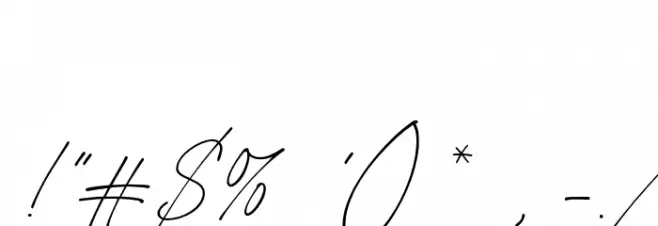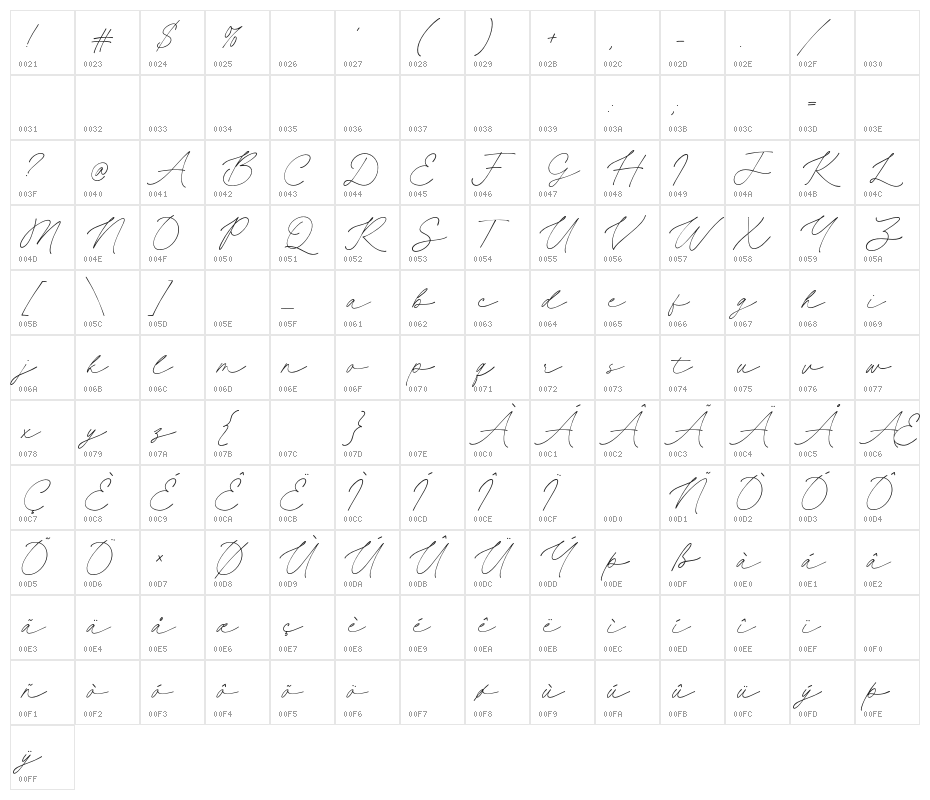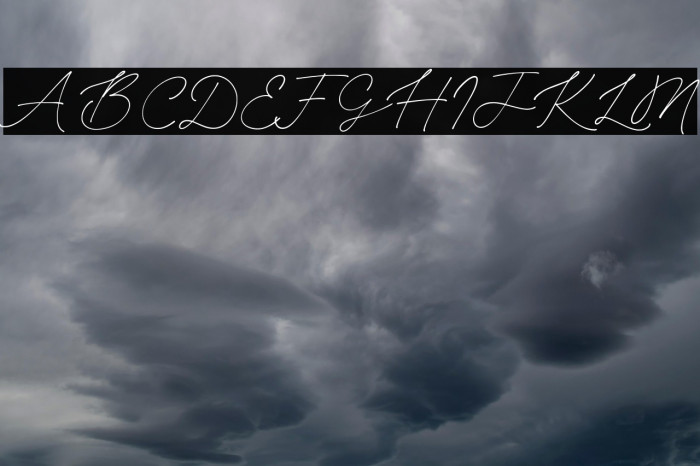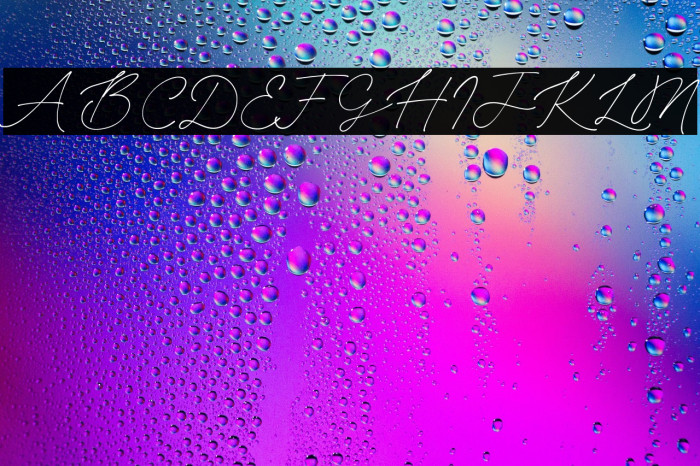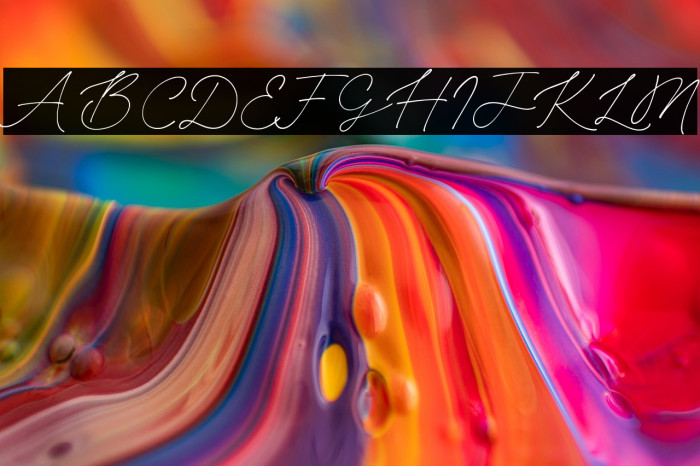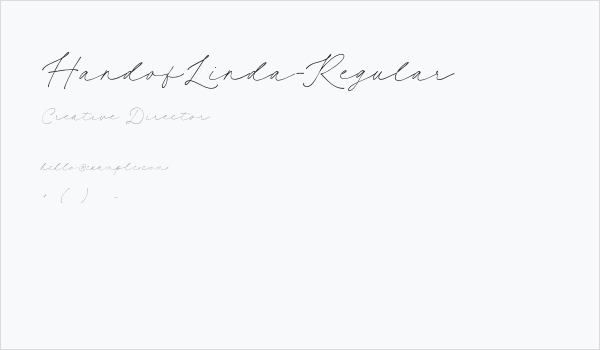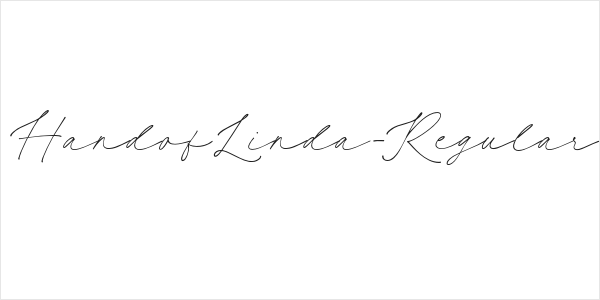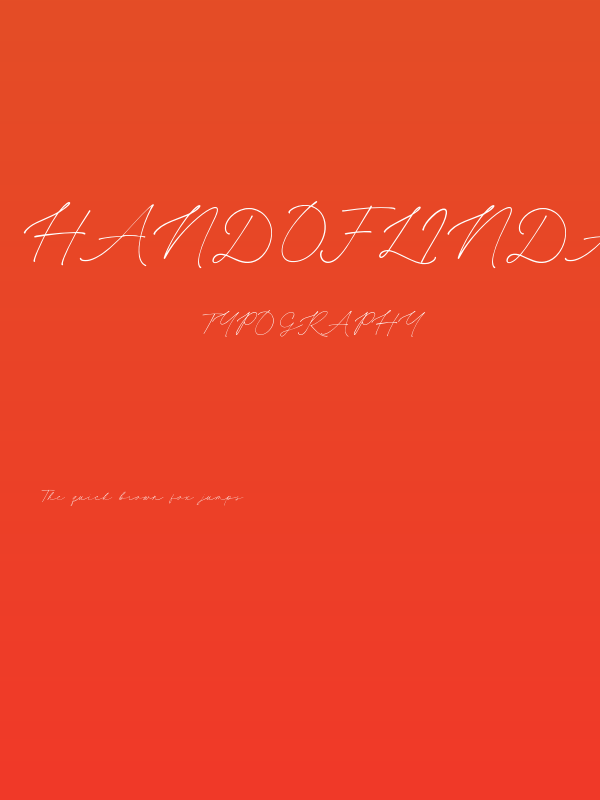
HandofLinda-Regular Font
| Famiglia di caratteri | Hand of Linda |
| Stile generale | Elegant |
| Caso d'uso | Logos, Invitations, Personal Correspondence |
| Progetti proposti | Ideal for wedding invitations, personal letters, greeting cards, and branding that requires a personal touch. |